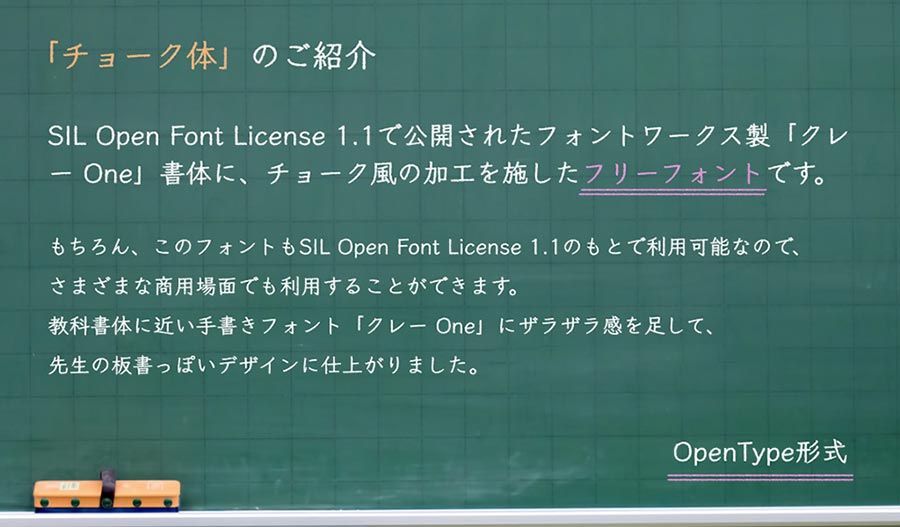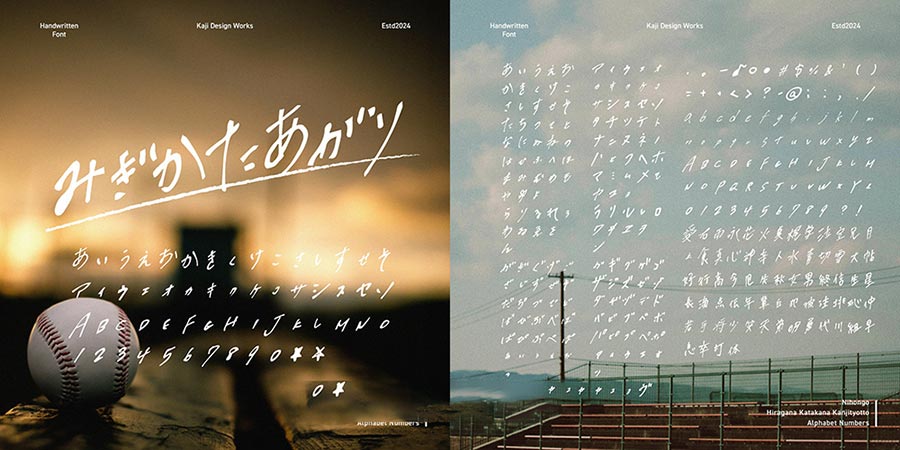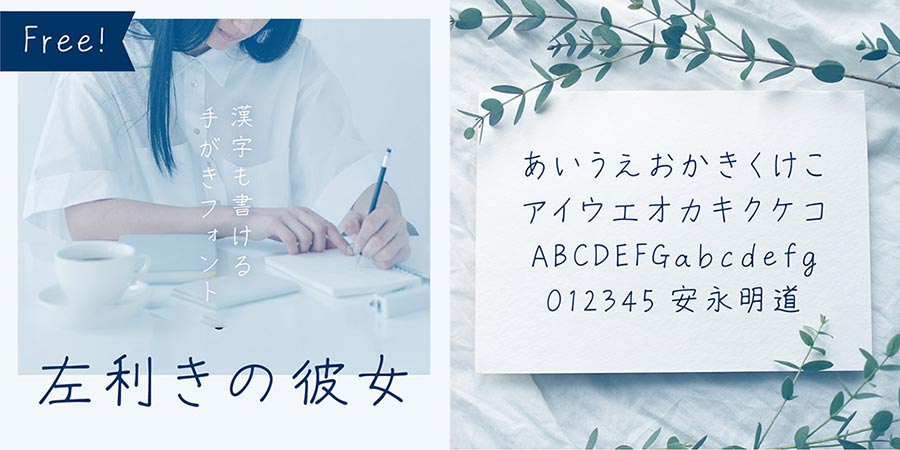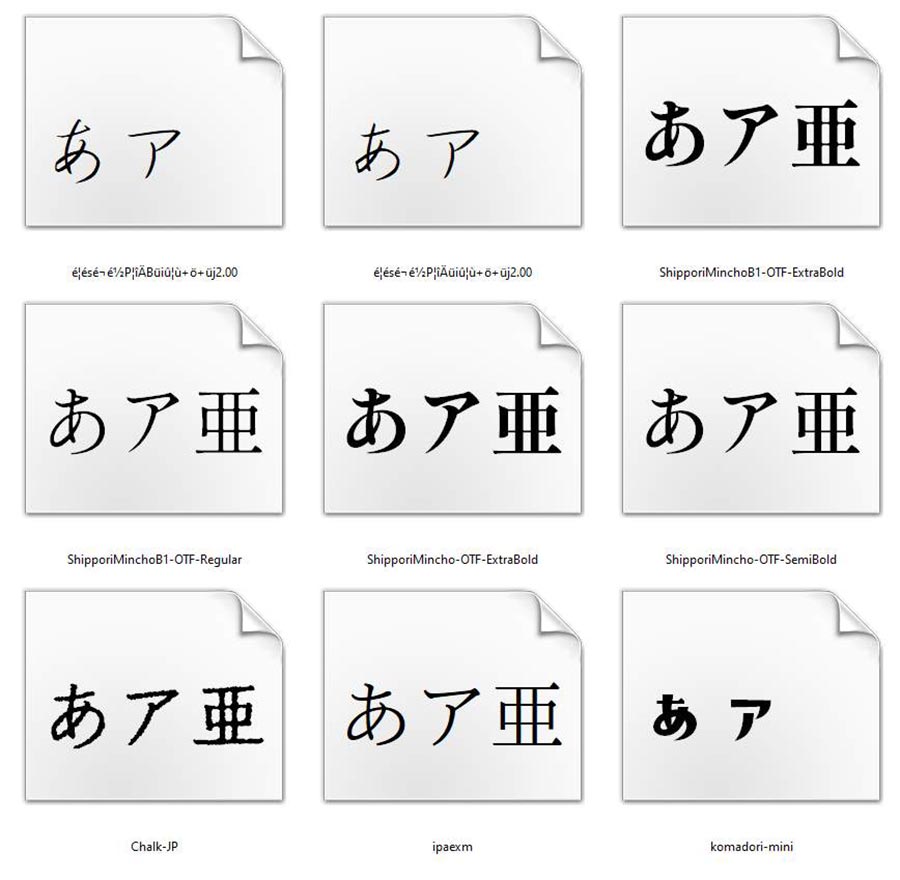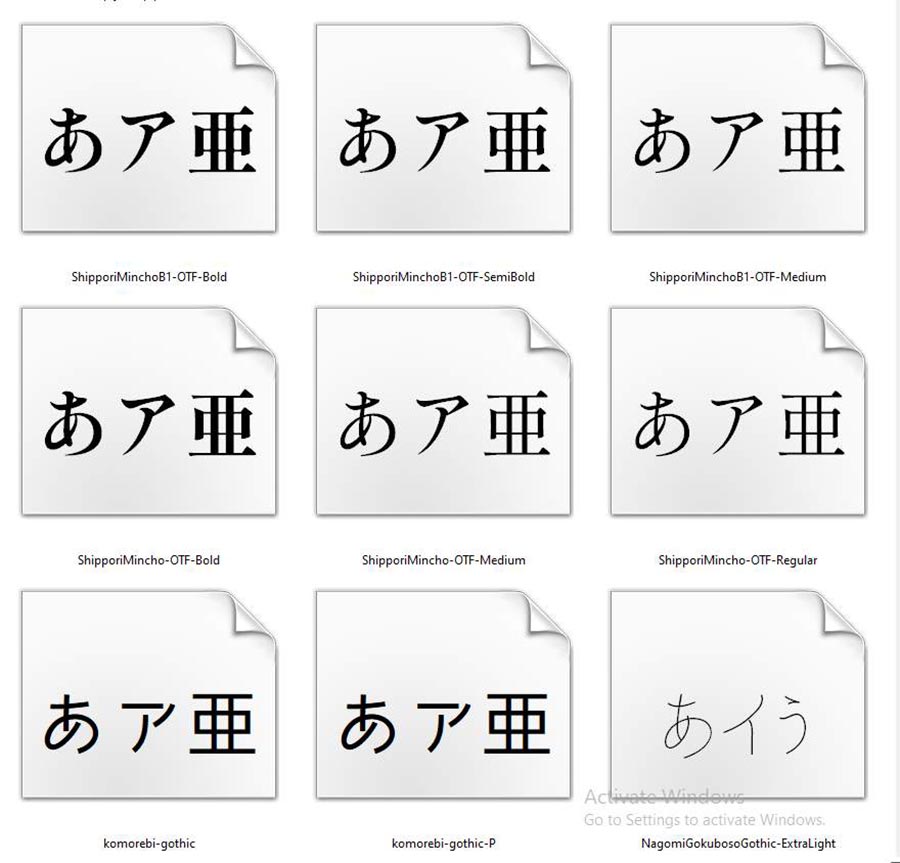
Chia Sẻ Tổng Hợp 10+ Font Chữ Tiếng Nhật Đẹp Miễn Phí
Font chữ tiếng Nhật là lựa chọn lý tưởng để mang lại nét đẹp tinh tế, độc đáo cho thiết kế mang đậm phong cách văn hóa sứ sở Hoa Anh Đào. Khám phá bộ sưu tập 10+ font chữ tiếng Nhật miễn phí từ Sadesign.vn để nâng cao chất lượng thiết kế của bạn. Các font chữ này thích hợp cho mọi loại dự án từ thiết kế đồ họa đến in ấn, website hay quảng cáo.
1. Tại Sao Nên Sử Dụng Font Chữ Tiếng Nhật?
Font chữ là yếu tố quan trọng trong việc truyền tải thông điệp và tạo dựng thương hiệu trong mọi dự án thiết kế. Đặc biệt, khi làm việc với các dự án liên quan đến văn hóa Nhật Bản, việc sử dụng font chữ tiếng Nhật đẹp không chỉ giúp tăng tính thẩm mỹ mà còn thể hiện đúng bản sắc văn hóa.
Trong bài viết này, Sadesign.vn sẽ chia sẻ với bạn 10+ font chữ tiếng Nhật miễn phí, giúp bạn dễ dàng áp dụng vào các dự án thiết kế của mình, từ website, poster, đồ họa đến bao bì sản phẩm. Việc chọn đúng font chữ không chỉ làm đẹp thiết kế mà còn giúp truyền đạt thông điệp một cách rõ ràng và ấn tượng. Từ những font chữ hiện đại đến những font chữ mang đậm phong cách truyền thống, bộ sưu tập này chắc chắn sẽ đáp ứng mọi nhu cầu sáng tạo của bạn.
2. Top 10+ Font Chữ Tiếng Nhật Đẹp Miễn Phí Từ Sadesign.vn
Font chữ tiếng Nhật có thể chia thành hai loại chính: KanjiHiragana. Kanji là hệ thống chữ tượng hình, trong khi HiraganaKatakana là hai bảng chữ cái âm tiết. Các font chữ tiếng Nhật thường kết hợp cả ba loại này để tạo ra sự hài hòa trong thiết kế. Tùy thuộc vào tính chất của dự án, bạn có thể chọn font chữ có sự kết hợp giữa các hệ thống chữ khác nhau. Tại Sadesign cung cấp mẫu 10 font chữ sau:
1. Noto Sans Japanese
Noto Sans Japanese là một trong những font chữ phổ biến nhất, được sử dụng rộng rãi trong thiết kế đồ họa và web. Font này có thiết kế đơn giản, dễ đọc và rất dễ dàng để phối hợp với các font chữ Latin. Đây là lựa chọn lý tưởng cho các dự án cần sự hiện đại và tối giản.
2. Sawarabi Gothic
Sawarabi Gothic là một font chữ không chân mang lại cảm giác hiện đại, phù hợp cho các dự án thiết kế thương hiệu hoặc quảng cáo. Font này có thiết kế sắc nét, làm nổi bật các chi tiết và dễ dàng nhìn thấy ở các kích thước nhỏ.
3. Kokoro
Kokoro là một font chữ mang phong cách viết tay, mang đến một cảm giác nhẹ nhàng, dễ thương. Đây là lựa chọn tuyệt vời cho các dự án thiết kế liên quan đến trẻ em, sản phẩm dễ thương hay các chiến dịch quảng cáo phong cách Nhật Bản.
4. Hannari
Với những đường nét mềm mại và nhẹ nhàng, Hannari là một font chữ rất phù hợp cho các thiết kế mang phong cách vintage hoặc phong cách Nhật Bản cổ điển. Font này rất thích hợp cho các ấn phẩm nghệ thuật, bìa sách hay poster phim.
5. Yu Gothic UI
Yu Gothic UI là một font chữ hiện đại với độ tương phản thấp, mang lại cảm giác thoải mái khi đọc. Font này thích hợp cho các trang web, ứng dụng di động hoặc các ấn phẩm cần sự chính xác và dễ tiếp cận.
6. M PLUS 1p
M PLUS 1p là một font chữ thanh thoát, mang đậm ảnh hưởng của các font chữ phương Tây nhưng vẫn giữ được sự dễ dàng và rõ ràng của chữ tiếng Nhật. Đây là một lựa chọn tuyệt vời cho các thiết kế hiện đại, quảng cáo sản phẩm hay các trang web cần sự nhẹ nhàng nhưng đầy cá tính.
7. Mochiy Pop P One
Nếu bạn đang tìm kiếm một font chữ phong cách hoạt hình, Mochiy Pop P One là sự lựa chọn tuyệt vời. Với các nét chữ tròn trịa và dễ thương, font này rất phù hợp với các dự án thiết kế liên quan đến manga, anime hoặc các sản phẩm dành cho giới trẻ.
8. Kosugi Maru
Kosugi Maru là một font chữ tròn đầy, dễ thương nhưng cũng rất dễ đọc. Font này có thể được sử dụng trong nhiều loại dự án, từ poster quảng cáo đến thiết kế bao bì sản phẩm, đặc biệt là các sản phẩm dành cho đối tượng trẻ em hoặc các thương hiệu muốn tạo hình ảnh gần gũi và thân thiện.
9. Teko
Teko là một font chữ sans-serif với các nét chữ dày và mạnh mẽ, mang lại sự uy nghiêm và đẳng cấp. Font này rất phù hợp cho các dự án thiết kế đòi hỏi sự nổi bật, như logo, banner quảng cáo hay các thiết kế web.
10. Karla
Karla là một font chữ sans-serif rất dễ đọc và hiện đại. Với thiết kế đẹp mắt và gọn gàng, Karla là sự lựa chọn lý tưởng cho các website hoặc các thiết kế truyền thông số, nơi yêu cầu sự đơn giản và dễ dàng tiếp cận.
Bộ sưu tập 10+ font chữ tiếng Nhật miễn phí từ Sadesign.vn là một tài nguyên tuyệt vời dành cho các nhà thiết kế, nghệ sĩ hoặc bất kỳ ai đang làm việc với các dự án có yếu tố văn hóa Nhật Bản. Các font chữ này sẽ giúp bạn tạo ra những sản phẩm thiết kế độc đáo, sáng tạo và đầy tính nghệ thuật. Hãy tải ngay các font chữ này và bắt tay vào sáng tạo các thiết kế tuyệt vời cho dự án của bạn! Hãy tải ngay 10+ Font Chữ Tiếng Nhật Đẹp Miễn Phí  này để làm mới và nâng tầm thiết kế của bạn! 🌸